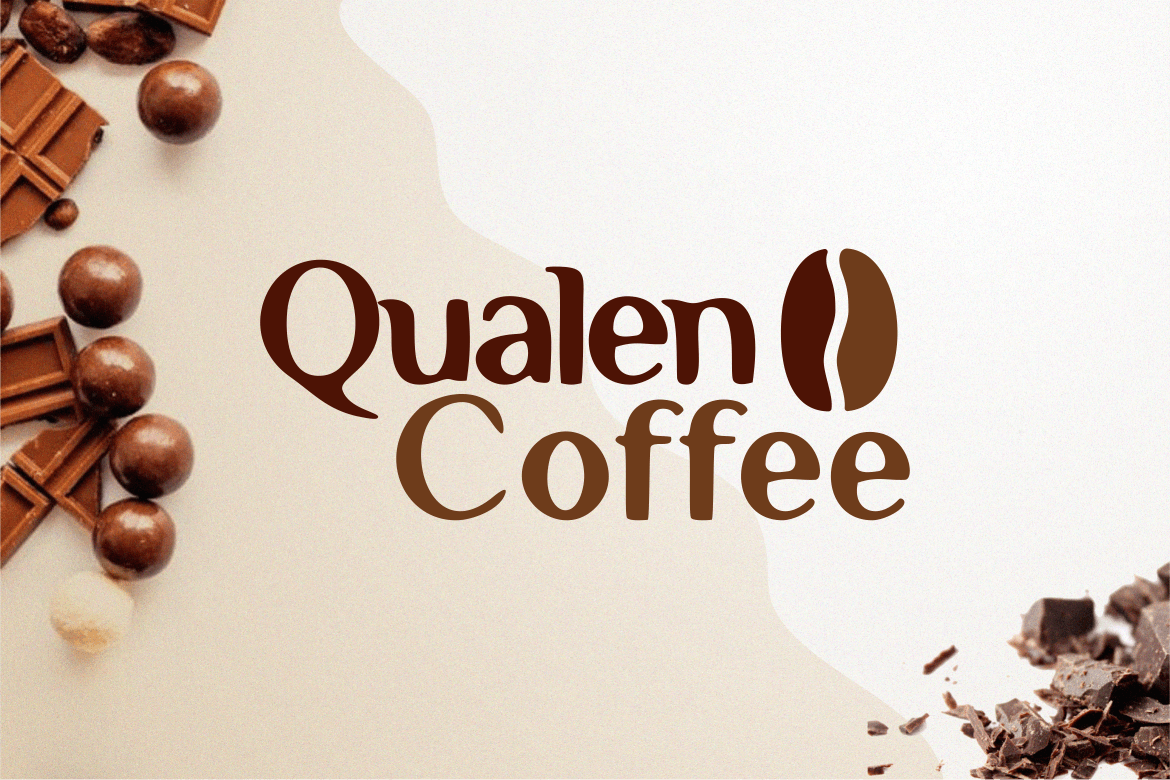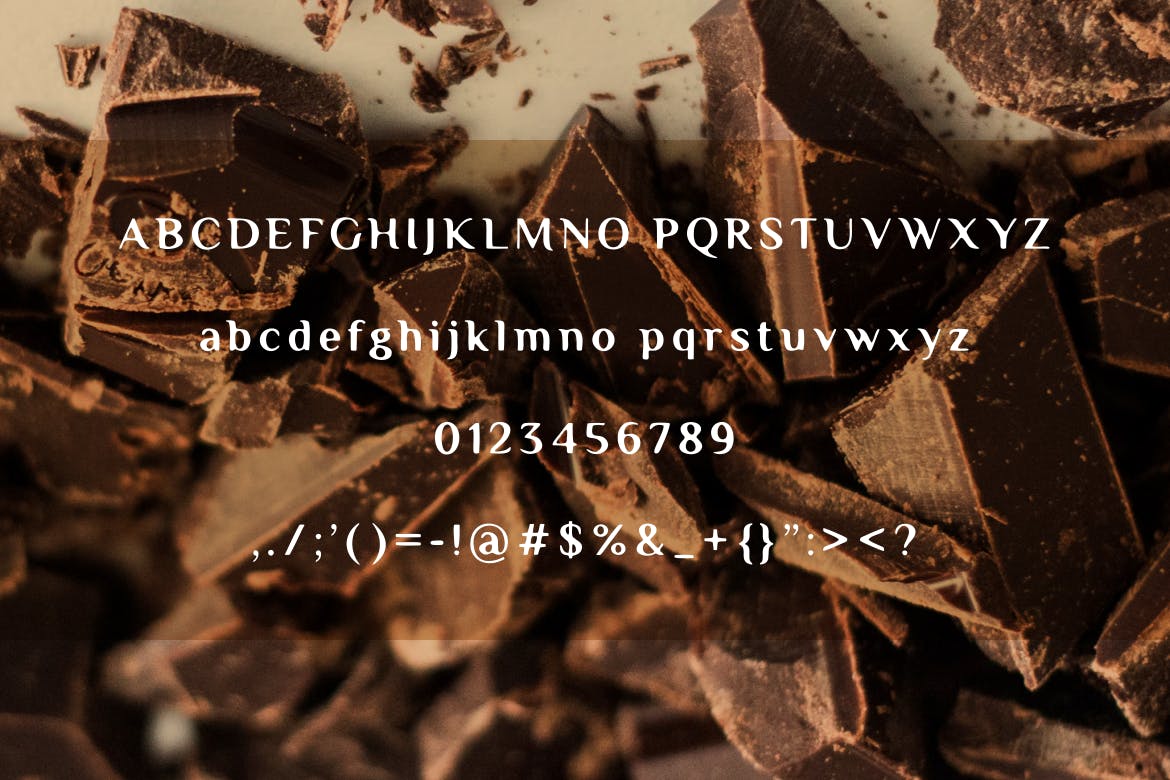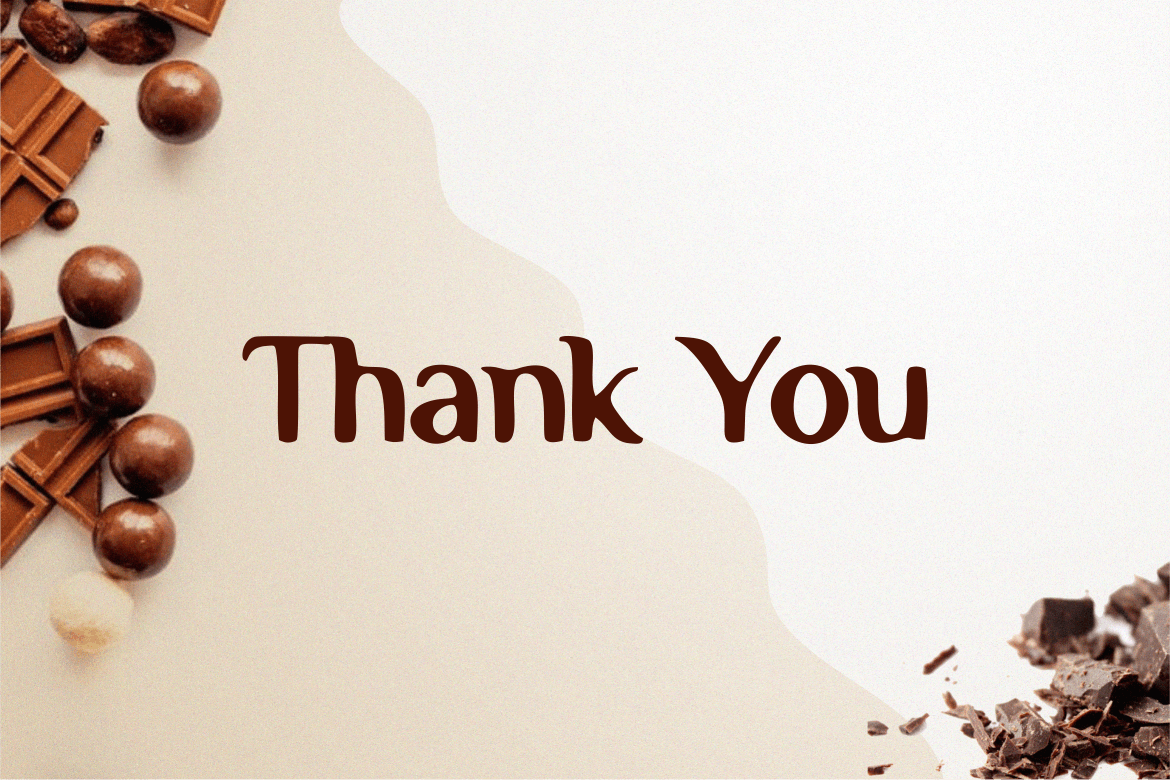
به معرفی محصول جدید خود یعنی فونت Coollattee - فونت مدرن میپردازیم.
فونت Coollattee - فونت مدرن، یک فونت نمایش جسور و اصیل است. این فونت برای هر پروژه برندینگ مانند طراحی لوگو، چاپ تیشرت، ورزشهای الکترونیکی و بسیاری دیگر مناسب است و در انواع مختلفی از زمینهها برجسته به نظر میرسد.